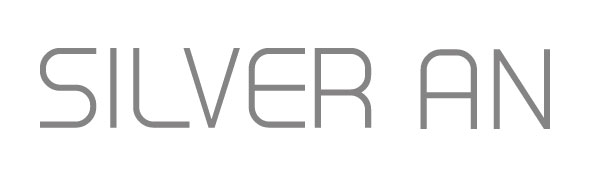
Rund und gerade - zum verrückt werden!
Benötige dringend hilfe wg. dieser Schrift (siehe Bild)
Es gibt etwa 20 Möglichkeiten, die immer an einem Buchstaben scheitern.
Wer weiß Rat????